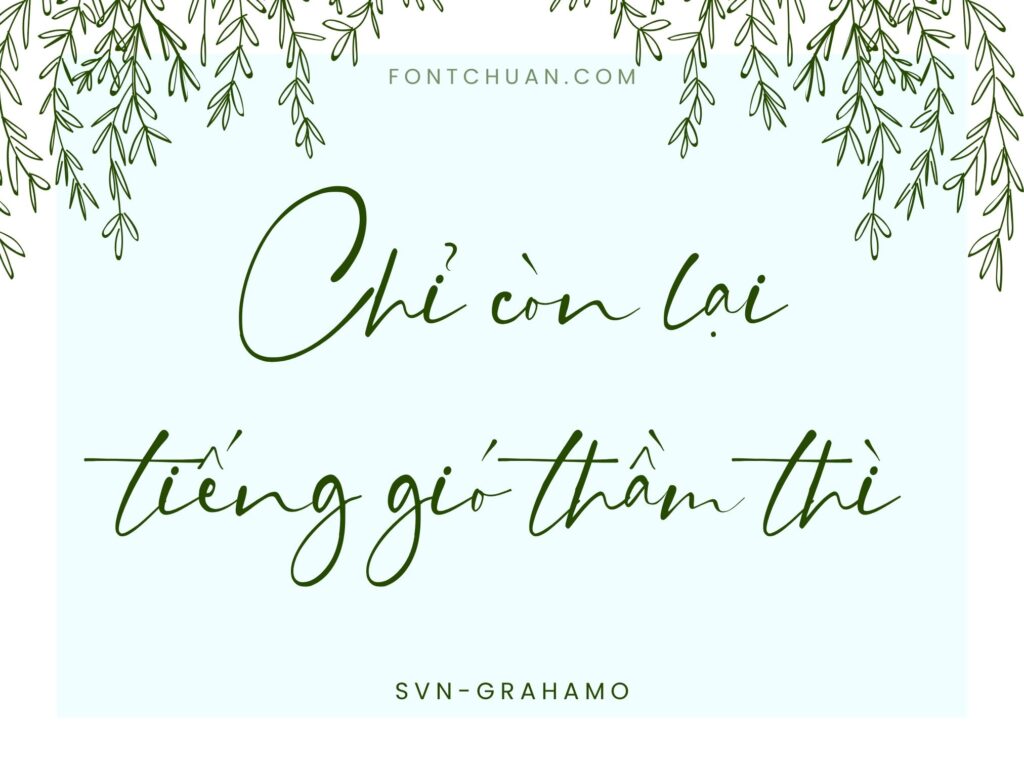
Font SVN Grahamo Việt Hóa
Tác giả Font: Candra Hamdani
Font SVN-Grahamo là phiên bản Việt hóa của kiểu chữ Grahamo, được thực hiện bởi Styleno.1 Fonts. Grahamo là một kiểu chữ viết tay, mang phong cách tự nhiên và thân thiện, tạo cảm giác như một ghi chú viết tay thực sự. Font này thích hợp cho nhiều mục đích sử dụng khác nhau, từ thiết kế thiệp mời, bao bì sản phẩm đến các ấn phẩm truyền thông.
SVN-Grahamo lý tưởng cho các dự án thiết kế yêu cầu sự gần gũi và cá nhân hóa, như thiệp mời, bao bì sản phẩm và các ấn phẩm truyền thông. Các ngành nghề như ẩm thực, spa và thiệp cưới có thể tận dụng font này để tạo điểm nhấn trong thiết kế. Ngoài ra, font cũng thích hợp cho các sự kiện như Tết, Valentine, Sinh nhật và các lễ hội khác.